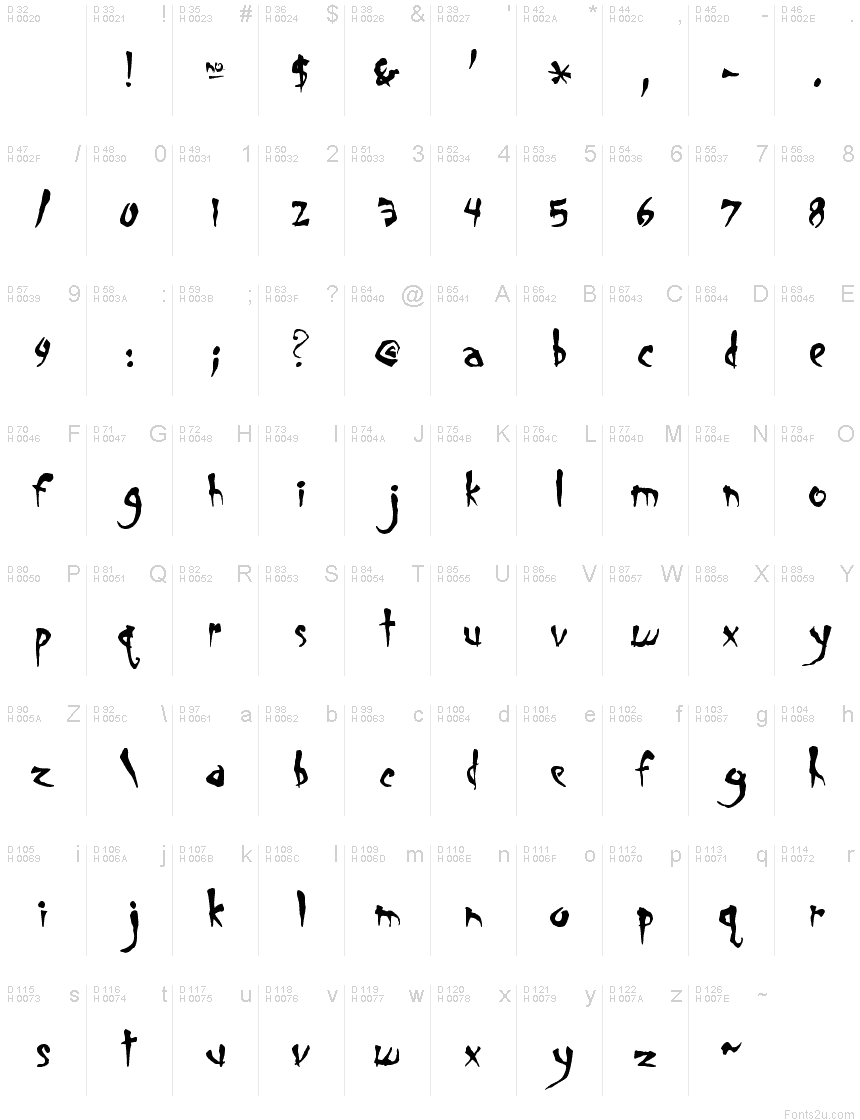
Smegalomania، وهو خط فرشاة مجاني من تصميم John Martz، يبدو كأنه حبر متمرد خُطّ على الصفحة بقلم تحديد ممتلئ. الحروف تتذبذب وتتضخم بضربات غير منتظمة تكاد تكون وحشية، مع منحنيات طويلة ووصلات سميكة وملطخة تمنح الخط طابعاً مضطرباً وخاماً وجريئاً بعض الشيء.
هذه الطاقة الخشنة مثالية لعناوين الملصقات، وأغلفة المجلات المستقلة، ومنشورات الفرق الموسيقية، وعناوين أفلام الرعب، واسكتشات الشعارات البانك، حيث قد تبدو الخطوط العادية أكثر من اللازم. كخط مجاني، فإنه يعمل بشكل أفضل في الجمل القصيرة، لأن إيقاع الفرشاة المتقطع والمنحنيات المبالغ فيها تقوم بمعظم العمل.